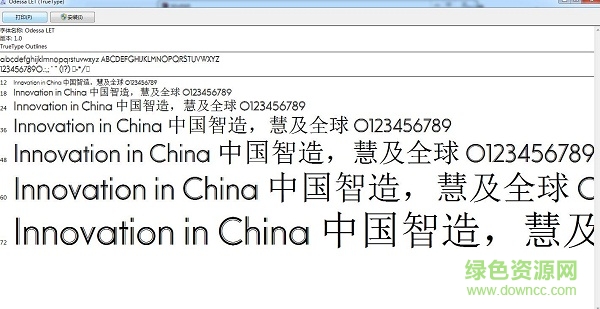
odessaletplain字體
odessa let字體是一款突破常規(guī)的英文個(gè)性字體,字體線條都是雙線設(shè)計(jì),內(nèi)深外淺,結(jié)構(gòu)平穩(wěn),適用于娛樂、平面設(shè)計(jì)、影視等行業(yè)用字,有需要者快來本站免費(fèi)下載吧!